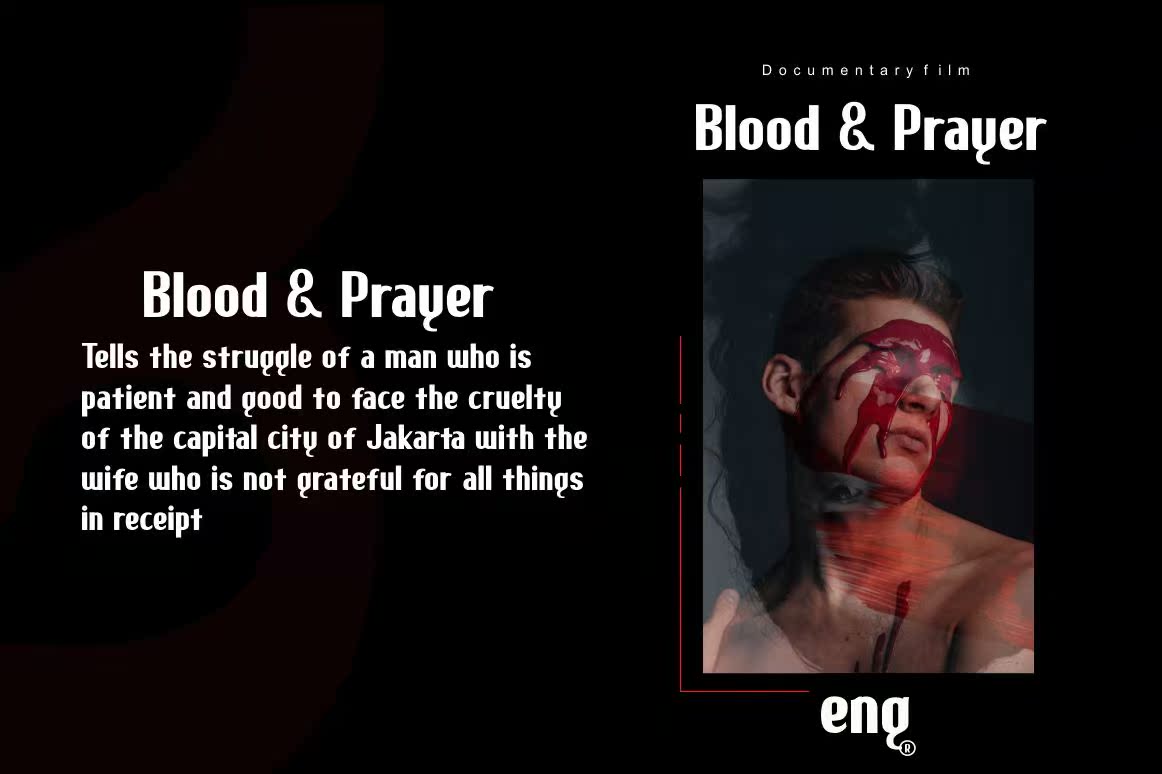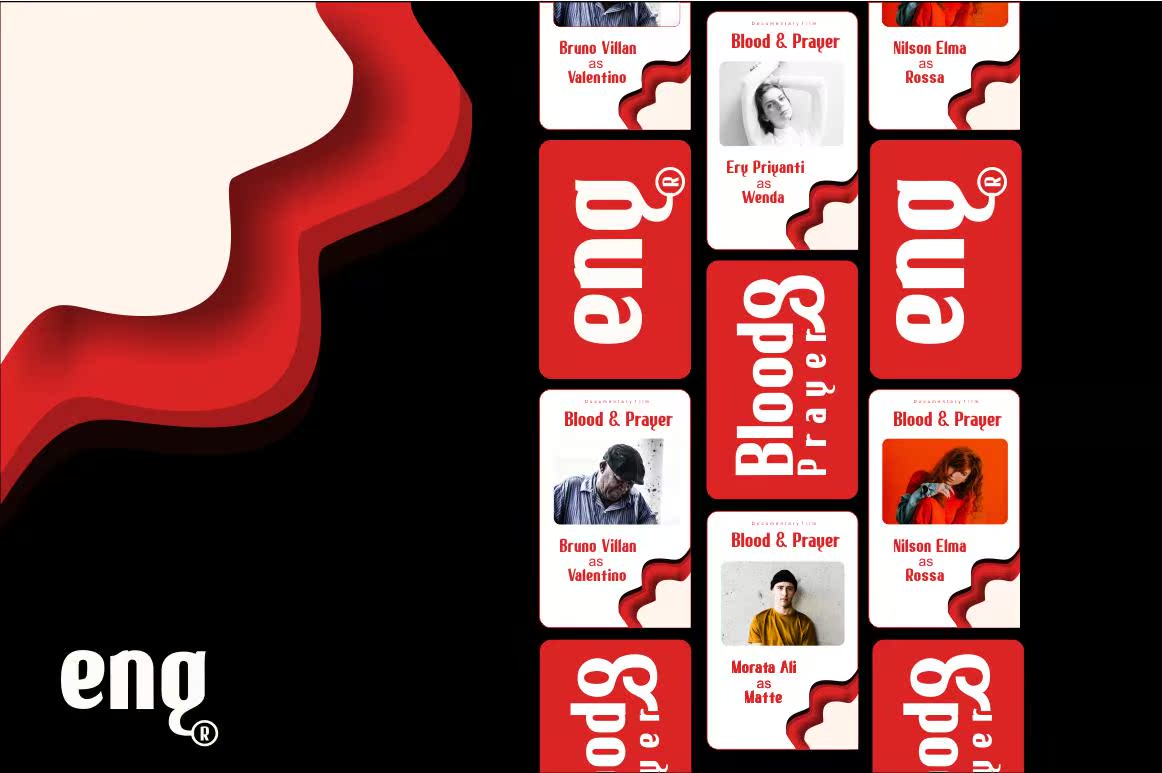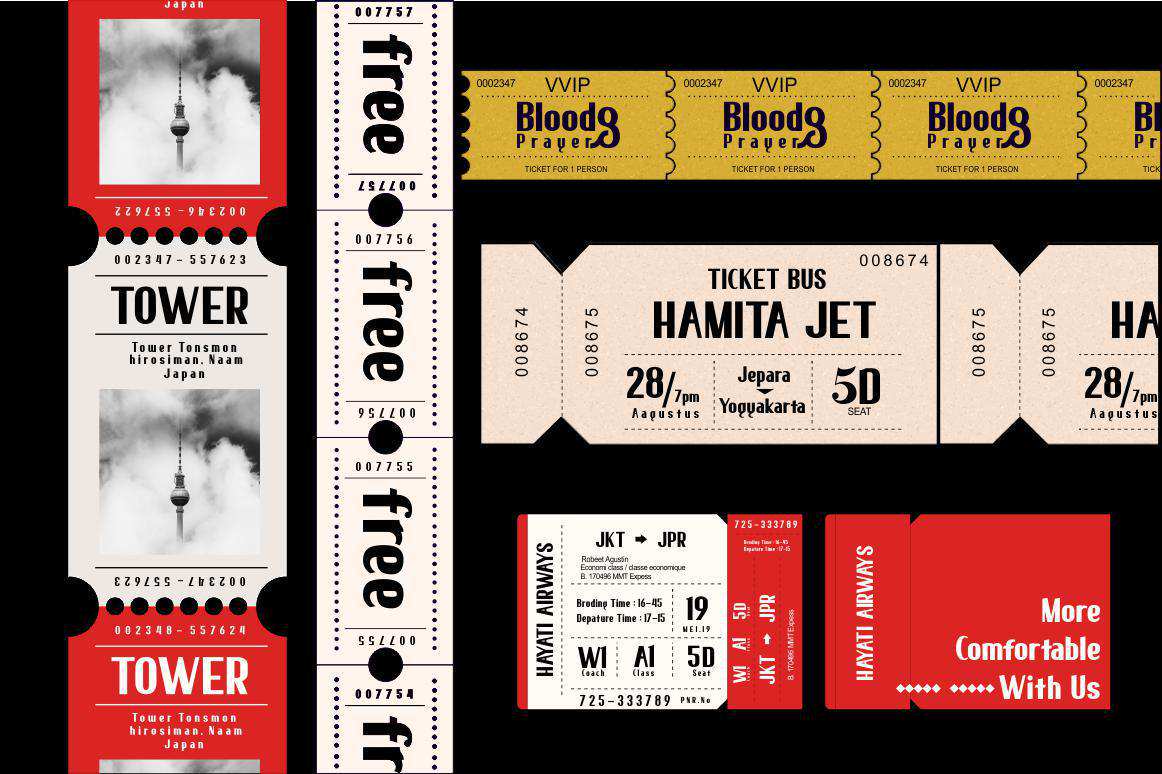
他还介绍了ElmaeLegantFont,它是一种现代的LegantFont,它是一种由这些字体组成的集合,每个字体都有自己的特点,可以在任何情况下为您设计,包括个人资料、海报、标识、电影封面、名片、门票、邀请函、书籍和照片,使用您的字体可以简化您的项目,包括哪些内容?他将介绍ElmaeLegantFontswithoutserif,它是一种现代的LegantFont,是一种由这些字体和字体组成的集合,有其自身的特点,在任何情况下为您设计,包括个人资料、海报、标识、电影封面、名片、门票、邀请函、书籍等,用你的字体可以简化你的项目包括什么?